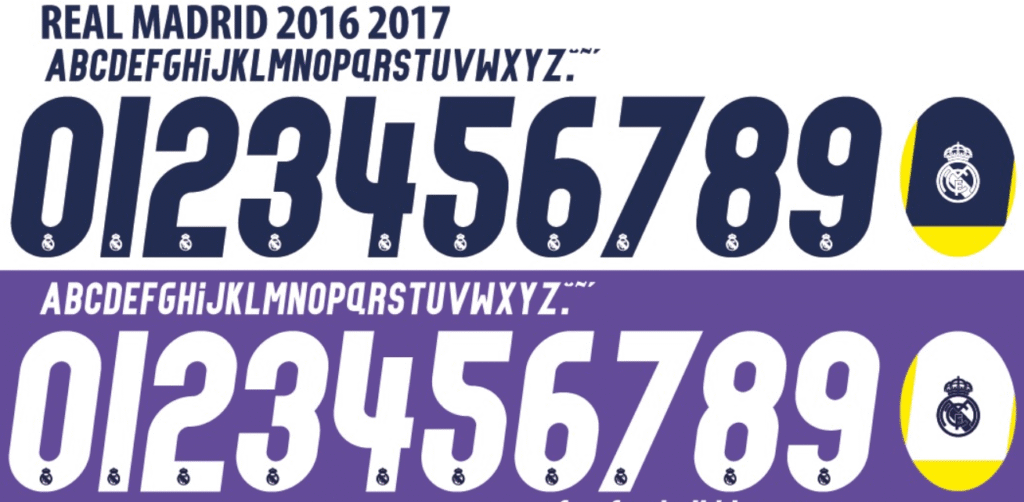
Relembre a era de ouro do futebol europeu. A temporada 2016-2017 ficará para sempre marcada na história do Real Madrid não apenas pelo futebol de gala comandado por Zinedine Zidane, mas pela conquista da histórica “La Duodécima” (12ª Champions League) e do título da La Liga.
Para os designers e personalizadores que buscam recriar o manto vestido por lendas como Cristiano Ronaldo, Sergio Ramos e Marcelo, trazemos hoje a tipografia oficial desenvolvida pela Adidas para aquele ano inesquecível. Esta é a fonte exata usada nas competições europeias e nas copas, perfeita para estampar a camisa branca clássica ou o elegante uniforme roxo (Away).
Estilo Visual e Aplicação
A tipografia de 2016-17 da Adidas rompeu com os estilos mais “quadrados” de anos anteriores. Ela apresenta um design sans-serif levemente condensado, com curvas suaves e cortes modernos que transmitem dinamismo e velocidade.
É uma fonte que oferece excelente legibilidade à distância. No uniforme titular (Home), ela foi aplicada em um tom de azul/roxo vibrante, criando um contraste perfeito com o branco merengue. Já no uniforme reserva (o famoso kit roxo), a fonte aparecia em branco, destacando-se pela elegância. É indispensável para quem quer reproduzir com fidelidade as camisas da final de Cardiff contra a Juventus.
Dica de Design: Ao criar mockups ou estampas, utilize esta fonte também para recriar camisas comemorativas da Champions League, pois essa tipografia se tornou sinônimo da hegemonia do Real Madrid na Europa.